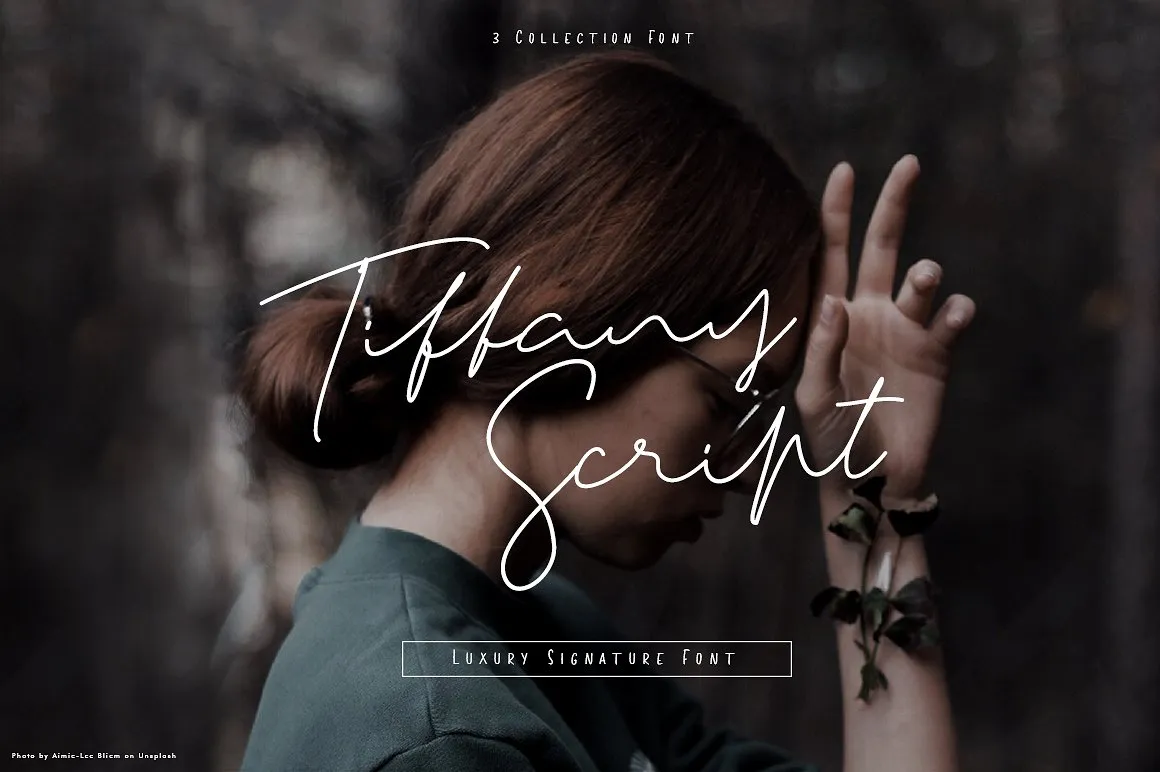
Tiffany Handwritten Font – Download Grátis
A Tiffany Handwritten Font é uma elegante escolha para designers que buscam personalidade e sofisticação em seu trabalho. Essa fonte, criada pelo designer zziplex, traz a essência de um autêntico desenho a mão, com traços simples, elegantes e extremamente belos. Tiffany é perfeito tanto para uso nas marcas quanto para criar rótulos, especialmente aqueles que buscam uma atmosfera naturalmente elaborada. A fonte Tiffany tem três estilos variados, oferecendo um caráter muito peculiar na versão mais expressiva. Isso a torna ideal para todas as necessidades de projeto da marca, seja em criações visuais complexas ou simples e elegantes. Esta é uma escolha conveniente para quem busca tanto sofisticação quanto originalidade em suas marcas digitais. A Tiffany Handwritten Font é perfeita para criar um toque distintivo em logo design, apresentações de slides, cartões de visita e materiais promocionais – sempre mantendo a autenticidade do desenho a mão. Evidenciando sua beleza natural e elegância, ela se destaca como uma opção perfeita para aqueles que buscam um estilo único em suas criações digitais.